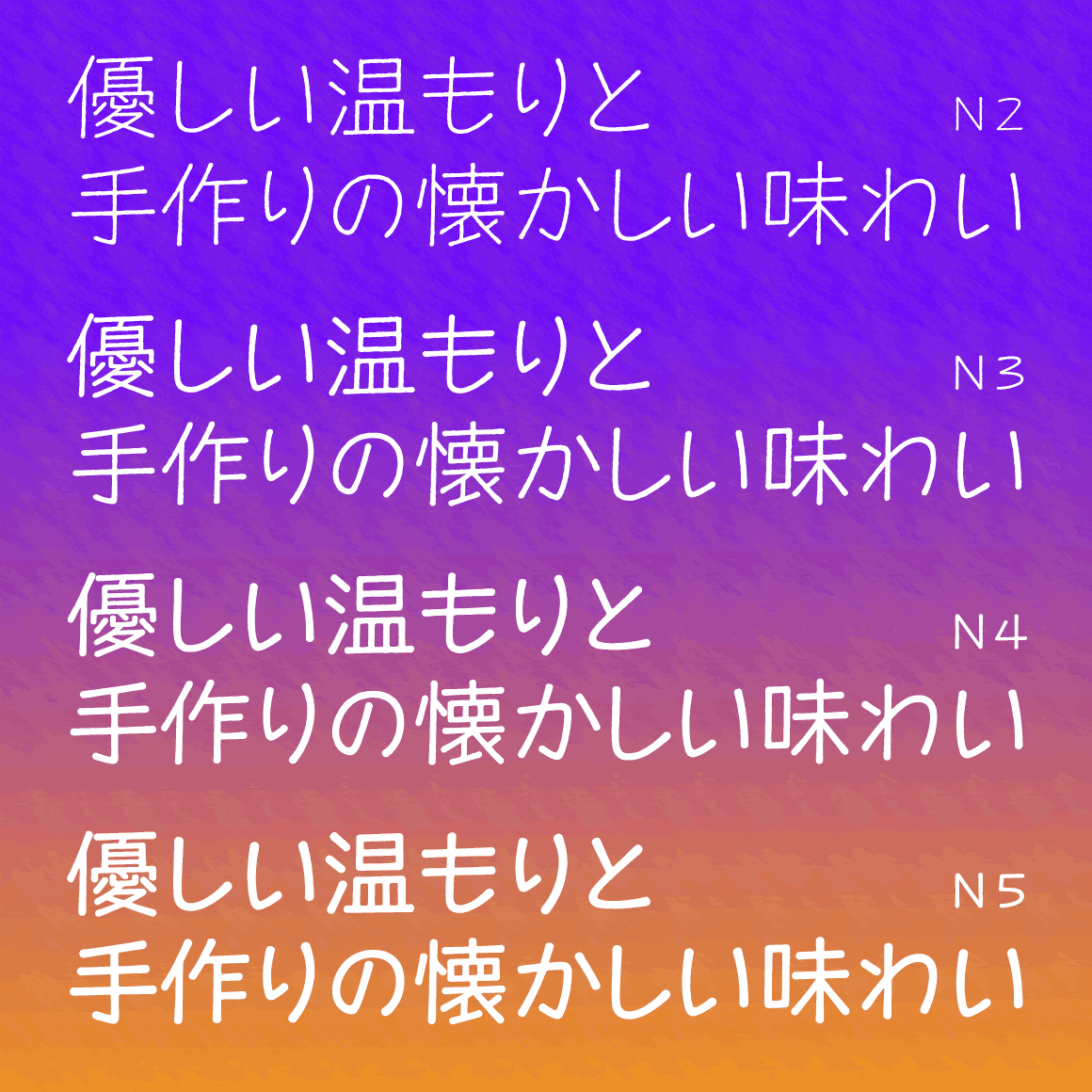
セプテンバー清音教漢N2〜5(無料お試し版)
セプテンバーN2〜5(商品版)
| デザイン |
細いペンで小さく描いた文字を元に、仕上げました。 デジタルフォントは、キレイでツルンとしたプラスチック製品のようなイメージがありますが、この書体の文字の輪郭は微妙にデコボコで、手作りの味わいがあります。 ペン習字書体のような気取ったものではありません。 もっと親しみやすく読みやすく、気持が素直に届くようにデザインしたつもりです。 あなたの願いや思いをこのフォントで伝えてください。 等幅バージョンは、英大文字のアイ「I」と英小文字のエル「l」や数字のいち「1」、そして英大文字のオー「O」と数字のゼロ「0」がはっきり区別がされているので、URL表記やプログラム編集などに最適です。 NEC特殊文字とIBM拡張文字も使えるようになりました。 |
連想されるイメージ 寄せられたコメントから抜粋 |
人のぬくもり・手書き風なのに知的・ちょっと懐かしい・すごく柔らかい・詩的な味わい・ガリ版文字・映画字幕みたい・優しい・癖があるけど読みやすい・見てるだけで楽しい・こんなフォント見たことない・嫌味がない・ほんわかしている・アナログな雰囲気がいい・カジュアル・微妙なでこぼこが新鮮・「る」がイイ・自然で上品・ひとつひとつの文字に表情がある・友達に手紙を書きたくなった・気持ち良い軽さ |